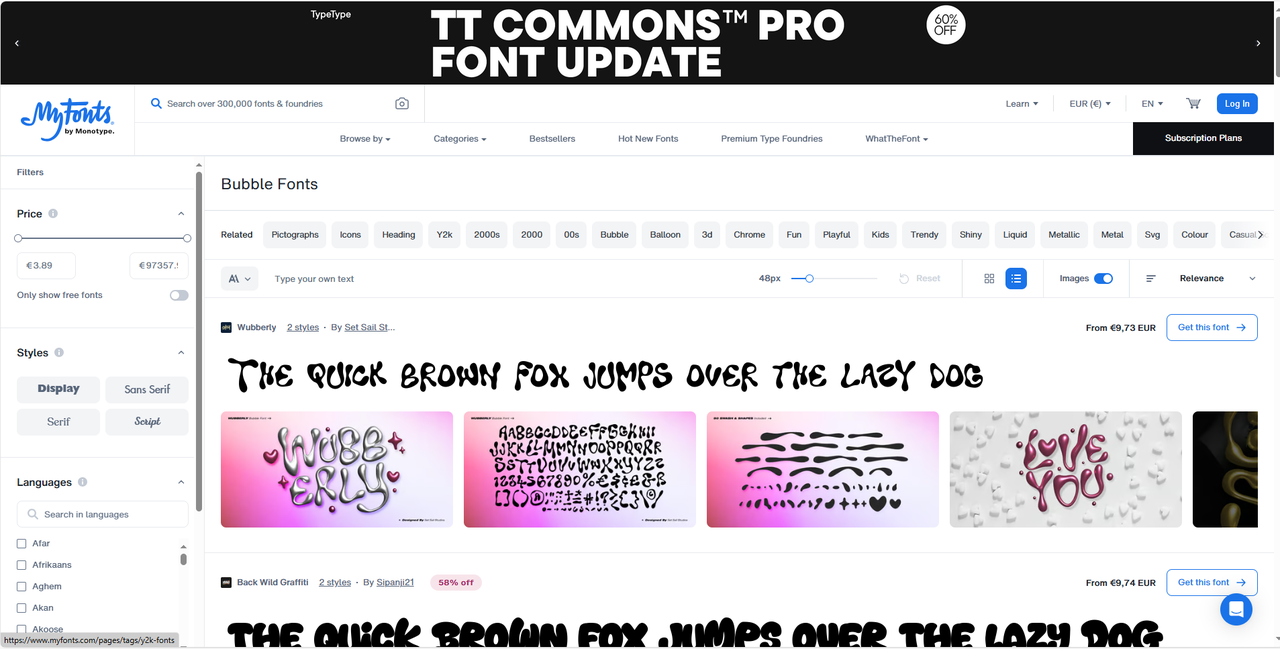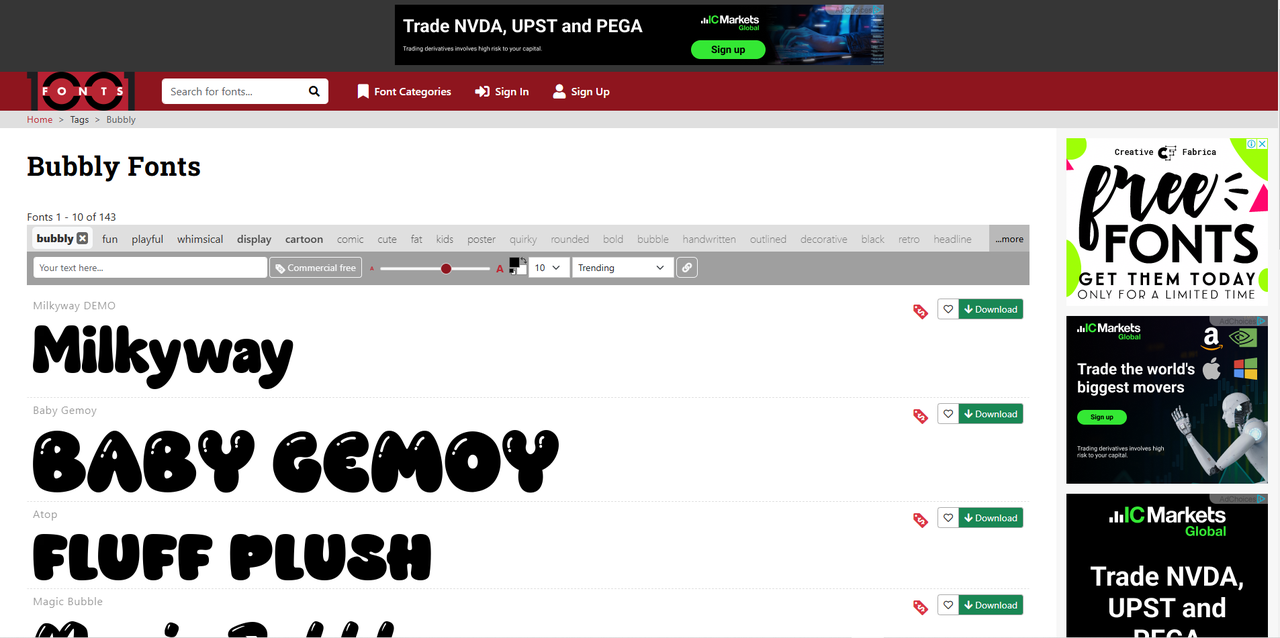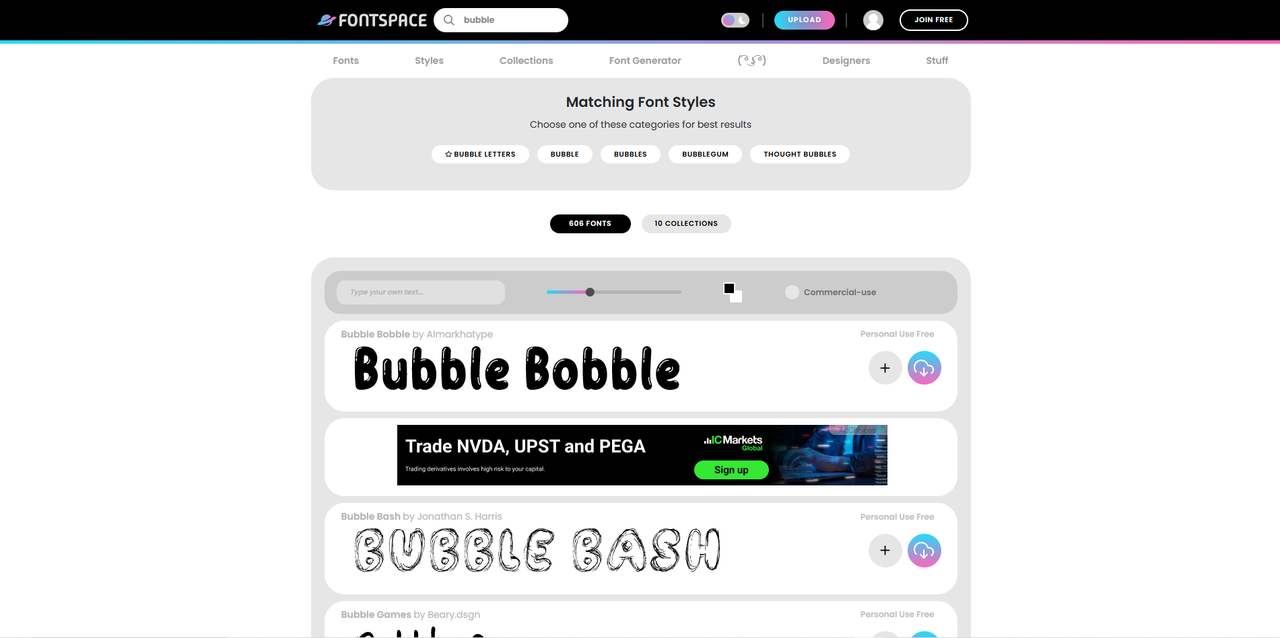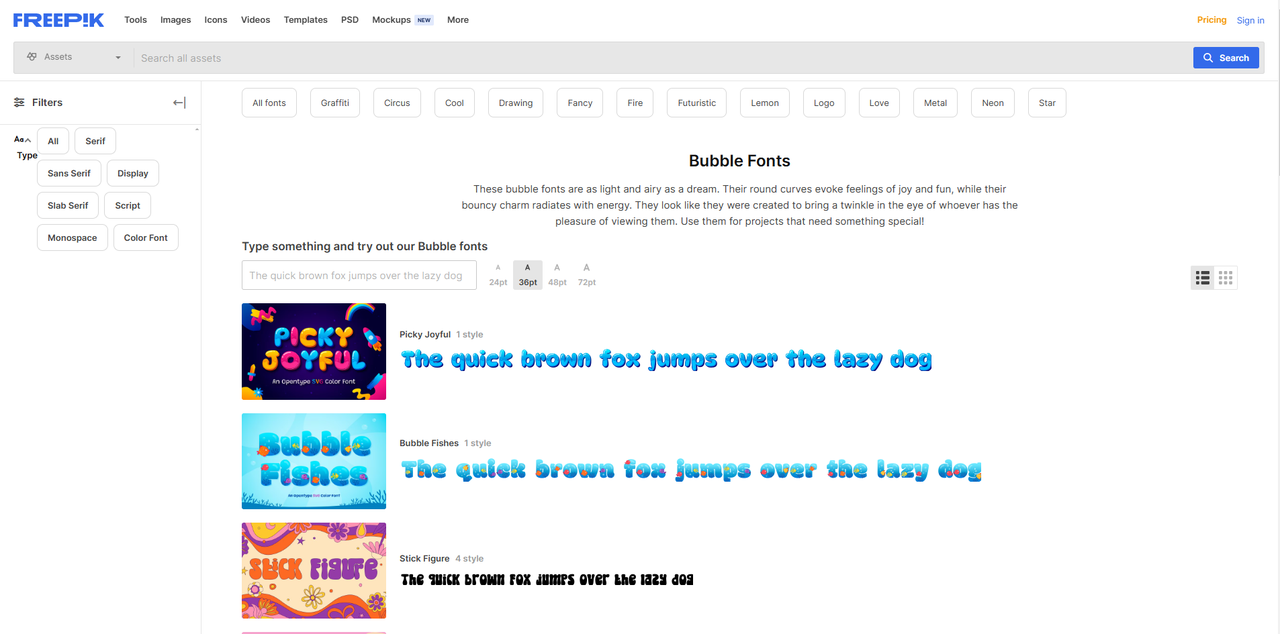
الخط الفقاعي هو أسلوب نصي ممتع وممتع غالبًا ما يستخدم في التصميمات التي تهدف إلى جذب الانتباه أو خلق أجواء فاترة. يمكنك العثور عليه في دعوات حفلات الأطفال ولافتات مواقع الويب والملصقات ورسومات الوسائط الاجتماعية. يجعل نوع الخط هذا رسالتك تبرز بمظهرها المستدير والجريء والشامبانيا.
زيادة المشاركة الخاصة بك على الانترنت مع أفضل الخطوط فقاعة
يمكن أن يكون تعزيز مشاركتك عبر الإنترنت أمرًا سهلاً باستخدام خيارات التصميم الصحيحة. يعد استخدام خط نصي فقاعي إحدى الطرق لإبراز المحتوى الخاص بك. يجذب هذا الأسلوب الممتع والجريء الانتباه ويضيف شخصية إلى مشاركاتك. دعنا نستكشف كيف يمكن لهذه الخطوط أن تعزز تواجدك على الإنترنت.
الاستخدامات الشائعة للخط فقاعة كبيرة
الحروف الفقاعية الكبيرة ممتعة ومتعددة الاستخدامات في العديد من المشاريع الإبداعية. من ثقافة البوب إلى الإعلان ، يضيفون لمسة مرحة تجذب الانتباه. دعونا نلقي نظرة على بعض الاستخدامات الأكثر شيوعًا للأبجدية في الحروف الفقاعية:
• ثقافة البوب
هذه الخطوط شائعة في الكتب المصورة والبرامج التلفزيونية والأفلام لإبراز النص. يضيفون الطاقة ، خاصة في مشاهد الحركة أو اللحظات المضحكة. تساعد الأبجدية في الأحرف الفقاعية على خلق إحساس نابض بالحياة وممتع.
• العلامات التجارية والشعارات
تستخدم العلامات التجارية كتابة الفقاعات ثلاثية الأبعاد لإضفاء طابع ودود وودود على هويتها. تساعد هذه الخطوط في إنشاء شعارات لا تُنسى يسهل التعرف عليها. تجعل الحروف المستديرة والجريئة العلامات التجارية تبدو أكثر جاذبية وجاذبية لجمهور أوسع ، وخاصة المستهلكين الأصغر سنًا.
• دعوات الحزب
تعد خطوط الفقاعات المجانية مثالية لدعوات الحفلات ، خاصة لأعياد ميلاد الأطفال أو الأحداث غير الرسمية. يجعل الأسلوب الجريء والمرح النص بارزًا ، ويسلط الضوء على التفاصيل الرئيسية مثل التاريخ والمكان. علاوة على ذلك ، يمكنهم إضافة لمسة عصرية ، مما يجعل الدعوة تبدو منعشة ومثيرة.
• مشاريع التصميم الجرافيكي
سواء كنت تنشئ ملصقات أو منشورات أو تصميمات رقمية ، فإن خطوط الفقاعات الكبيرة تجعل الرسالة تنبثق. إنها مثالية لإضافة عنصر ممتع إلى أي مشروع. يساعد استخدام خط الفقاعات ثلاثي الأبعاد في التصميمات على إبقاء الأشياء خفيفة ومبهجة ، مما يجذب انتباه المشاهد بشكل إبداعي.
• الإعلان والترقيات
في الإعلانات ، تساعد رسائل الفقاعات الجمالية في جذب انتباه العملاء المحتملين. تجعل الحروف الجريئة والمستديرة الرسالة تبرز بشكل هزلي. يجعل الخط الفقاعي العروض الترويجية تشعر بالمرح والمشاركة ، وتشجع التفاعل.
• خطوط فقاعة قابلة للتخصيص
الاختيار من بين الخطوط المختلفة أو إنشاء واحد مع مولد الخط AI . تخصيص النص الخاص بك لجعلها تبرز في أي مشروع.
• تحرير النصوص المتقدم
يساعدك محرر النصوص متعدد الاستخدامات على تعديل حجم النص ولونه ونمط الخط ليناسب موضوع الفيديو الخاص بك. يمنحك هذا التحكم الكامل في مظهر النص الخاص بك.
• مزامنة الصوت مع النص على الفور
قم بمزامنة النص مع الصوت بسرعة ، مما يضمن المحاذاة السلسة مع التعليق الصوتي أو المؤثرات الصوتية. يساعد هذا في إنشاء تجربة مشاهدة سلسة.
• توليد بسيط لتحويل النص إلى كلام
تحويل النص إلى كلام دون الحاجة إلى أدوات تسجيل إضافية. تتيح لك هذه الميزة بسهولة إضافة السرد أو التعليق الصوتي إلى الفيديو الخاص بك.
• إضافة تسميات توضيحية تلقائية إلى مقاطع الفيديو
استخدم مولد التسمية التوضيحية التلقائي لإنشاء ترجمات فورية لمقاطع الفيديو الخاصة بك ، مما يجعل الوصول إلى المحتوى الخاص بك أكثر سهولة وتحسين تفاعل المشاهد وفهمه.
1. كيف تؤثر أحرف الفقاعة الرائعة على قابلية القراءة في واجهات المستخدم ؟
يمكن أن تجعل الأحرف الفقاعية الرائعة النص بارزًا ولكنها قد تقلل من قابلية القراءة إذا تم الإفراط في استخدامها في واجهات المستخدم. قد يكون من الصعب قراءة طبيعتها المرحة بأحجام صغيرة أو تخطيطات معقدة. من الضروري الموازنة بين الإبداع والوضوح للحصول على تجربة مستخدم سلسة. للحصول على نص واضح وجذاب بصريًا ، يوفر محرر فيديو سطح المكتب CapCut خطوطًا أنيقة وسهلة القراءة.